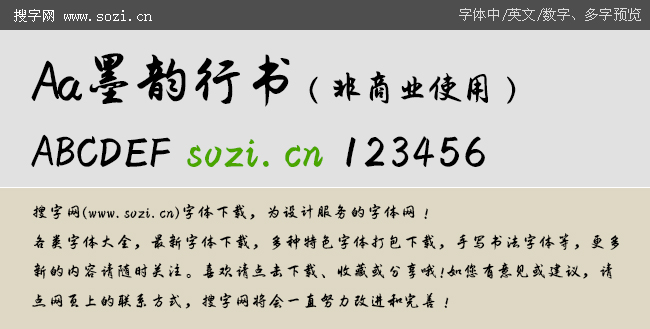
Aa墨韻行書
搜字網(wǎng)給大家提供一款A(yù)a墨韻行書(非商業(yè)使用)中文字體下載,Aa墨韻行書是一款國風(fēng)手書字體,,該字體書寫流暢,較少連筆,結(jié)構(gòu)比較工整,具有很好的視覺感。適合應(yīng)用于藝術(shù)設(shè)計、平面宣傳設(shè)計、網(wǎng)頁設(shè)計、海報設(shè)計等應(yīng)用(此字體為個人非商用版,商用可以聯(lián)系QQ:1006760504)。